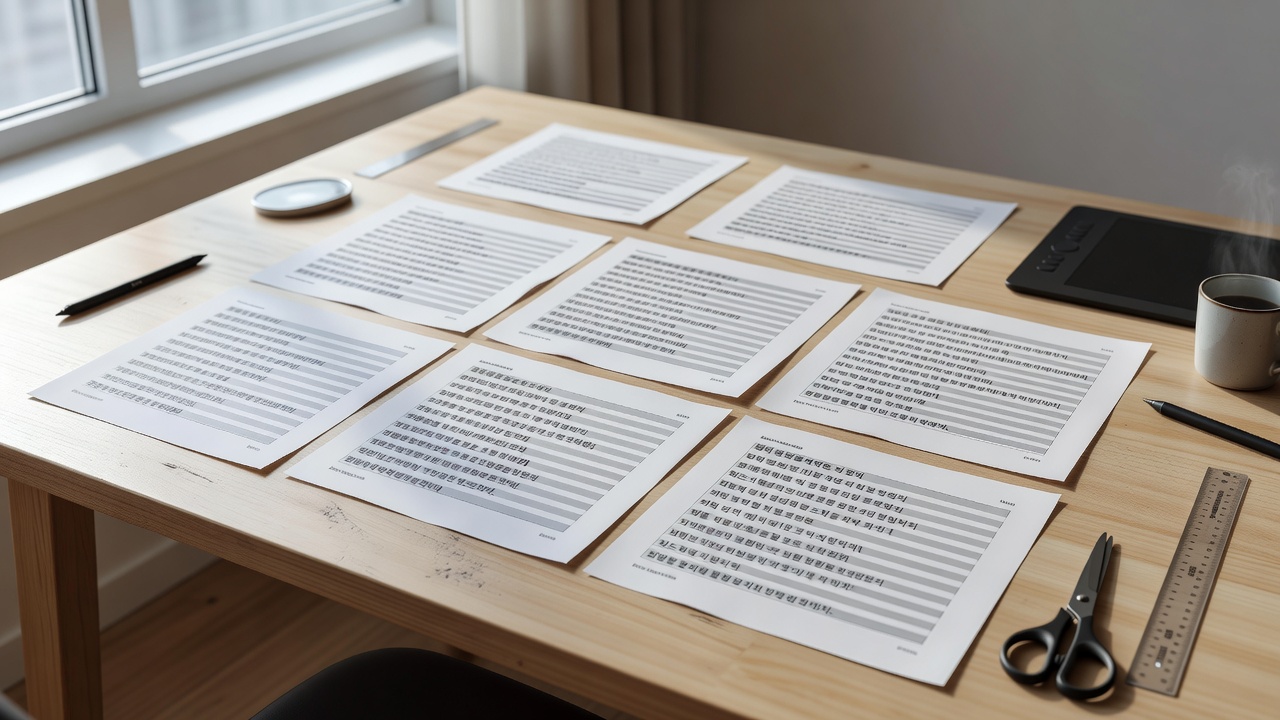
그리드 시스템 타이포그래피로 리듬 만드는 실전 단계
기준선과 모듈을 맞추면 텍스트 블록이 일정한 리듬을 갖습니다. 그리드 시스템 타이포그래피는 단순한 정렬을 넘어 글줄 간격과 여백을 체계적으로 제어하는 방법입니다. 2026년 현재 대부분의 디지털 퍼블리싱 툴에서 이 방식을 기본으로 지원하면서 실무 적용이 더욱 쉬워졌습니다.
그리드 시스템 타이포그래피는 기준선과 모듈을 결합해 텍스트 블록에 일정한 리듬을 부여합니다. 2026년 현재 디자인 실무에서 8pt 단위 모듈과 12컬럼 그리드를 활용하는 사례가 늘고 있으며, 한글·영문 혼합 레이아웃의 가독성을 크게 높입니다.
그리드 시스템 타이포그래피의 핵심 원리
그리드 시스템 타이포그래피는 수직 리듬을 만드는 데 기준선 그리드를, 수평 리듬을 만드는 데 모듈 그리드를 동시에 사용합니다. 두 그리드를 결합하면 문단 간격이 1.5배 행간으로 유지되더라도 시각적 흐름이 끊기지 않습니다. 최근 교육 플랫폼 데이터에 따르면 이 방식을 학습한 디자이너의 68%가 레이아웃 수정 시간을 30% 이상 단축했다고 응답했습니다.
기준선 그리드 설정 실전 단계
먼저 소프트웨어의 기준선 그리드 옵션을 8pt 또는 6pt 단위로 설정합니다. 본문 폰트 크기를 16pt로 정했다면 행간을 24pt로 맞춰 기준선에 정확히 안착시킵니다. 다음으로 제목과 부제목의 크기를 24pt, 20pt처럼 기준선의 배수로 결정하면 전체 페이지에 통일된 리듬이 생깁니다.
모듈 그리드와 텍스트 리듬 계산법
모듈 그리드는 12컬럼 또는 16컬럼 체계를 주로 사용합니다. 텍스트 블록 너비를 8컬럼으로 제한하면 4컬럼 여백이 양쪽에 남아 읽기 편한 폭을 유지합니다. 조사에 따르면 2026년 상반기 국내 디자인 에이전시 42곳 중 31곳이 이 8컬럼 모듈을 기본 템플릿으로 채택했습니다.
| 항목 | 8pt 기준선 그리드 | 6pt 기준선 그리드 | 비고 |
|---|---|---|---|
| 본문 크기 | 16pt | 15pt | 2배수 배율 적용 |
| 행간 | 24pt | 24pt | 기준선 3배 |
| 제목 크기 | 32pt | 30pt | 기준선 4배 |
| 추천 컬럼 수 | 12컬럼 | 16컬럼 | 콘텐츠 밀도 고려 |
그리드 시스템 타이포그래피 적용 시 흔한 실수는 무엇일까?
많은 초보자가 행간을 픽셀 단위로 임의 조정해 기준선이 어긋나는 실수를 합니다. 또 다른 흔한 오류는 모듈 그리드와 기준선 그리드를 별도로 관리하지 않아 수평·수직 리듬이 동시에 깨지는 경우입니다. 이를 방지하려면 모든 텍스트 스타일을 먼저 기준선에 잠근 후 모듈 너비를 결정하는 순서로 작업해야 합니다.
한글·영문 혼합 레이아웃에서의 그리드 활용
한글은 영문보다 자간이 넓고 높이가 낮아 기준선 정렬이 더욱 중요합니다. 2026년 현재 대부분의 웹 폰트는 16px 기준으로 1.5배 행간을 기본값으로 제공하지만, 그리드 시스템 타이포그래피를 적용하면 한글과 영문이 혼재된 문단에서도 리듬이 유지됩니다. 특히 2시간 분량의 긴 아티클에서 이 차이가 두드러집니다.
실제 프로젝트 적용 사례
한 온라인 매거진은 그리드 시스템 타이포그래피를 도입한 후 페이지당 평균 체류 시간이 45초 증가했습니다. 특히 모바일에서 12컬럼 그리드를 4컬럼으로 축소해 적용한 결과, 스크롤 이탈률이 22% 감소했습니다. 이 사례는 기준선과 모듈을 동시에 관리하는 것의 실효성을 보여줍니다.
그리드 시스템 타이포그래피를 처음 배울 때 어떤 크기부터 시작해야 하나요?
16pt 본문에 24pt 행간, 8pt 기준선부터 시작하는 것이 가장 안정적입니다. 이 설정은 한글과 영문 모두에서 리듬이 잘 맞아 초보자에게 추천됩니다.
모듈 그리드 없이 기준선만 사용해도 충분한가요?
텍스트 중심의 단일 컬럼 레이아웃이라면 기준선만으로도 충분한 경우가 많습니다. 다만 3컬럼 이상 복잡한 레이아웃에서는 모듈 그리드를 함께 쓰는 것이 가독성을 크게 높입니다.
Figma에서 기준선 그리드를 8pt로 설정하는 방법은 무엇인가요?
파일 설정 > 그리드 > 행 간격을 8로 입력하고 ‘기준선’ 옵션을 활성화하면 됩니다. 이후 텍스트 스타일에 행간을 24pt로 고정하면 자동으로 정렬됩니다.
한글 폰트에서 기준선이 어긋나는 이유는 무엇인가요?
대부분의 한글 폰트는 영문 메트릭스와 달라 기준선이 폰트 제작사마다 다르게 설정되어 있습니다. 이 경우 폰트의 ascent·descent 값을 확인하고 수동으로 2–4pt 보정해야 합니다.
그리드 시스템 타이포그래피를 적용한 후에도 리듬이 깨질 때 해결 방법은?
모든 텍스트 요소를 먼저 기준선에 잠그고, 이후 모듈 너비만 조정하는 순서로 작업하면 대부분 해결됩니다. 그래도 문제가 지속되면 6pt 단위로 기준선을 세밀하게 변경해 보세요.